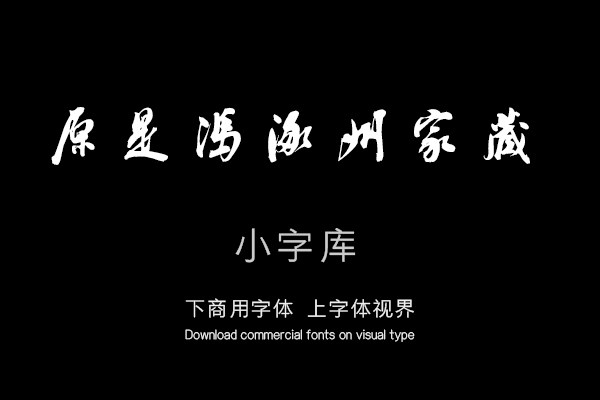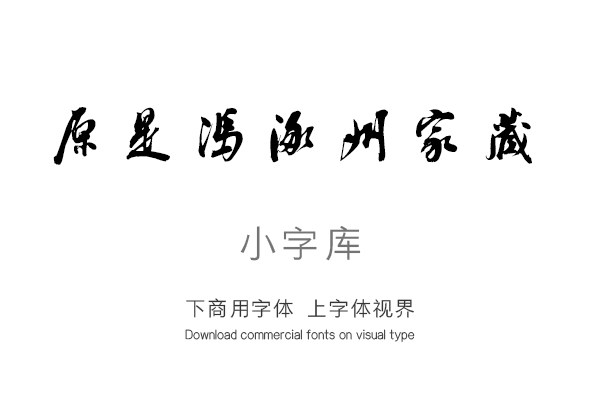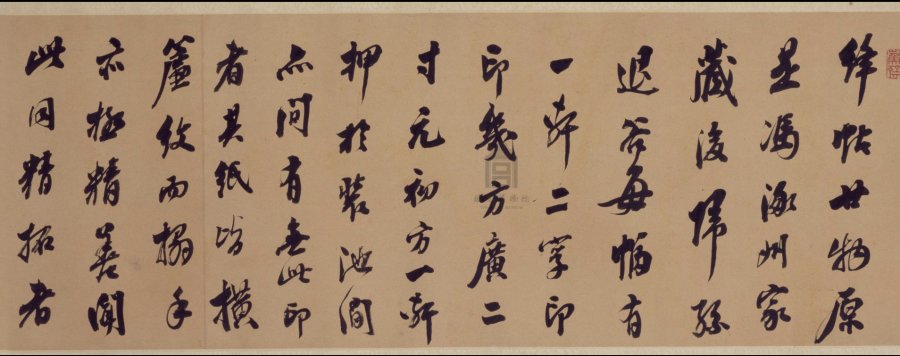
《汉标翁方纲论绛帖》是一款根据清代书法家翁方纲经典书法作品《论绛帖》卷,经过再次调整制作的小字库,该小字库共收录了该真迹作品中约276个字体。单字授权
绛帖廿物,原是冯涿州家藏,后归孙退谷。每幅有一轩二字印,印几方广二寸,元初方一轩押于装池间,亦间有无此印者。其纸皆横簾纹,而搨手亦极精善。闻此同精拓者凡数部,皆不全者。冯伯衡择其精善者合成此一部耳。其卷后皆仍存旧题识。十卷后复列帝王书,以宋太宗为首,二王书皆割裂,杂以头眩方诸帖矣。大观帖亦以冯伯衡所藏为真,今快雪堂帖所摹之旦极寒、追寻、建安诸帖及王廙、王洽诸迹,多是从大观真本出者。大观原石榷场本,每至边际破损处尤古雅可爱。今以快雪摹刻验之,如见秘阁真石之券。惜乎冯氏入石时,文敏未尝自跋其由大观真本摹出之原委,使后人无从而详考耳。己未初秋上澣 方纲。